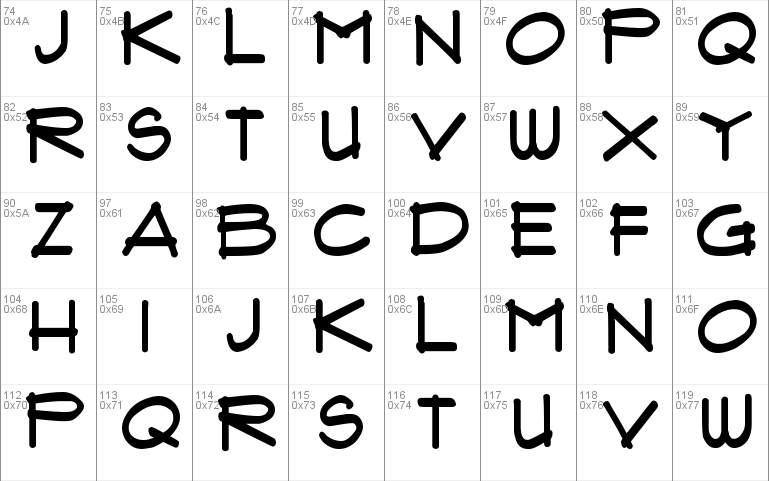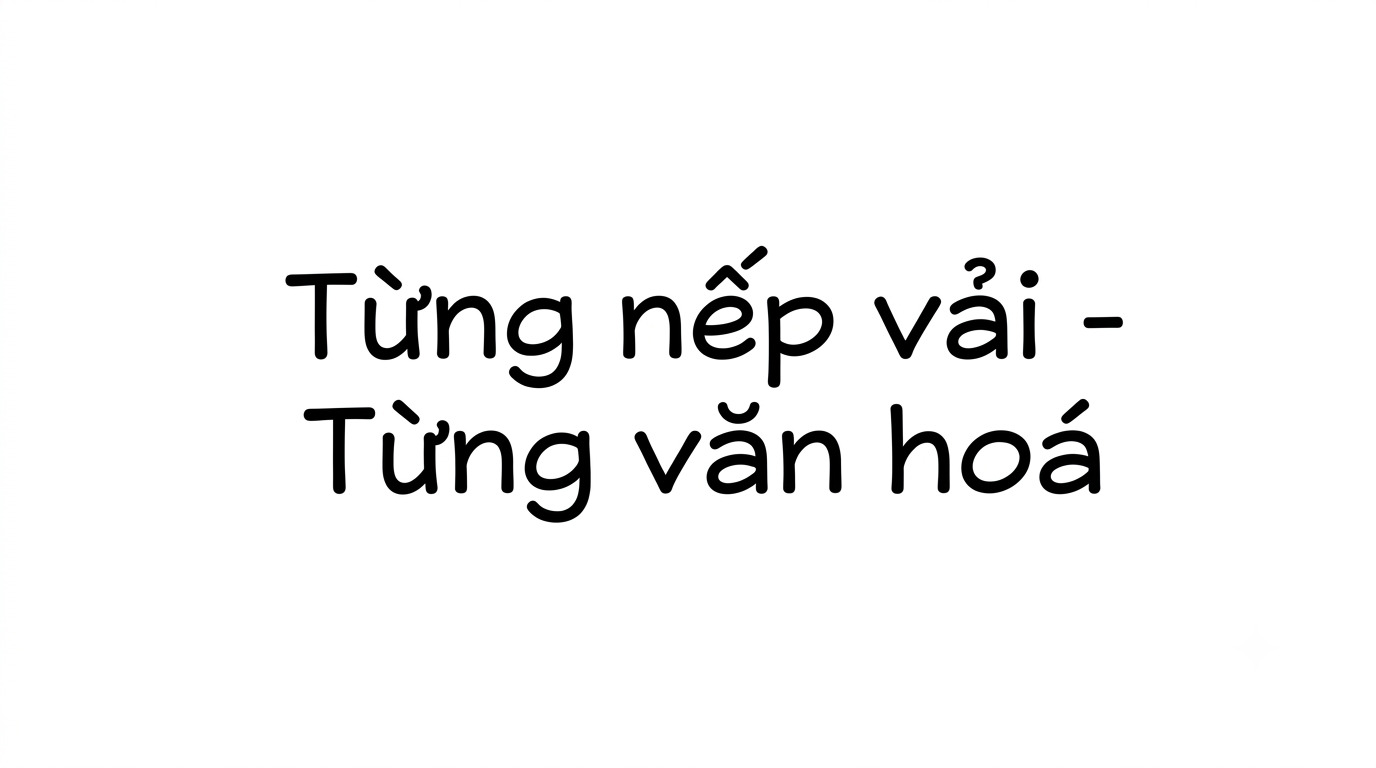
Font Flux Architect là gì?
Font Flux Architect là một phông chữ phong cách viết tay mô phỏng nét chữ của các kiến trúc sư trên bản vẽ kỹ thuật cổ điển. Đặc trưng của bộ chữ này là các đường nét dứt khoát, thanh thoát nhưng vẫn giữ được sự mềm mại tự nhiên, tạo cảm giác như được phác thảo trực tiếp bằng bút chì trên giấy can. Đây là sự lựa chọn cho các thiết kế hồ sơ năng lực công ty xây dựng, bìa bản vẽ, nhãn dán sản phẩm nội thất hoặc các mẫu quà tặng mang phong cách mộc mạc, hoài cổ.
Trong giới đồ họa, Flux Architect còn thường được tìm kiếm dưới tên gọi font architex hoặc các biến thể phông chữ kỹ thuật tương tự. Ưu điểm của dòng phông này là khả năng truyền tải thông điệp một cách chân thực, gần gũi nhưng vô cùng khoa học. Bản việt hóa tại In Viva đã được xử lý kerning cực chuẩn, đảm bảo các dấu thanh của tiếng Việt không bị chồng lấp lên các ký tự xung quanh, giúp bản thiết kế của bạn luôn rõ ràng và chuyên nghiệp trên mọi chất liệu.
Lưu ý: Khi bạn sử dụng font flux architect việt hóa cho thiết kế in ấn trên chất liệu gỗ hoặc kim loại, hãy chú ý đến độ tương phản để nét chữ viết tay không bị “nuốt” bởi vân gỗ hay bề mặt nhám.
5 Ứng dụng của font Flux Architect Việt hóa trong thiết kế và in ấn
Với phong cách chữ mô phỏng bản vẽ kỹ thuật và kiến trúc, Flux Architect giúp tạo dấu ấn riêng cho các ấn phẩm thương hiệu thuộc lĩnh vực xây dựng, nội thất và thiết kế:
- Thiết kế hồ sơ năng lực và bìa bản vẽ: Flux Architect phù hợp để sử dụng cho tiêu đề, tên dự án hoặc thông tin thương hiệu trên hồ sơ năng lực. Kiểu chữ mang hơi hướng kỹ thuật giúp tài liệu thể hiện sự chuyên nghiệp và đồng bộ với ngành kiến trúc, xây dựng.
- Khắc laser quà tặng gỗ doanh nghiệp: Logo hoặc tên thương hiệu dùng font Flux Architect khi khắc trên hộp trà gỗ, lịch gỗ để bàn hoặc bảng tên gỗ tạo cảm giác thủ công, gần gũi và phù hợp với các dòng quà tặng dành cho doanh nghiệp xây dựng, nội thất.
- Sản xuất bao bì sản phẩm nội thất và decor: Font chữ này có thể ứng dụng trên túi giấy Kraft, hộp giấy hoặc tem nhãn sản phẩm để thể hiện phong cách tối giản, phù hợp với các thương hiệu hướng đến thiết kế hiện đại và tinh tế.
- Thiết kế menu quán cafe phong cách Loft: Flux Architect Việt hóa phù hợp với các không gian mang phong cách công nghiệp, tối giản. Font có thể sử dụng trên menu gỗ, bảng thông tin hoặc các ấn phẩm trang trí giúp tăng tính đồng nhất cho không gian.
- In ấn quà tặng tri ân ngành kiến trúc: Lời chúc hoặc thông điệp sử dụng font Flux Architect khi in UV trên bình giữ nhiệt, sổ tay hoặc in nung trên bộ ấm chén sứ giúp món quà mang dấu ấn riêng dành cho kiến trúc sư, kỹ sư và đối tác.
5 lưu ý khi sử dụng font chữtrong in ấn
Để thiết kế sử dụng Flux Architect chuyển thành sản phẩm thực tế có độ rõ nét và phù hợp với từng phương pháp gia công, designer nên chú ý các yếu tố sau:
- Kiểm soát độ dày nét khi in ấn: Flux Architect có các đường nét mô phỏng chữ kỹ thuật tương đối mảnh. Khi in trên chất liệu có độ hút mực như giấy Kraft hoặc vải canvas, nên điều chỉnh độ dày Stroke phù hợp để hạn chế tình trạng mất nét.
- Tối ưu đường Path cho gia công bế nổi: Khi sử dụng Flux Architect để dập nổi logo trên hộp quà cao cấp, file vector cần được xử lý các điểm neo và đường nét nhỏ. Việc làm mượt đường Path giúp khuôn bế thể hiện rõ chi tiết chữ trên bề mặt giấy Ivory, giấy mỹ thuật hoặc carton lạnh.
- Lựa chọn kích thước chữ phù hợp: Flux Architect phù hợp với tiêu đề, logo hoặc các cụm từ ngắn. Với nội dung dài hoặc cỡ chữ quá nhỏ, các chi tiết kỹ thuật của font có thể làm giảm khả năng đọc khi in trên sản phẩm thực tế.
- Phối hợp màu sắc phù hợp với phong cách kiến trúc: Font này thường phù hợp với các gam màu như nâu gỗ, xám, đen, xanh đậm hoặc màu ánh kim. Việc lựa chọn màu sắc phù hợp giúp tổng thể thiết kế giữ được cảm giác hiện đại và chuyên nghiệp.
- Convert font trước khi gửi file sản xuất: Trước khi chuyển sang xưởng in, designer nên thực hiện lệnh Create Outlines để chuyển chữ thành dạng vector, hạn chế lỗi thay đổi font khi mở file trên các thiết bị khác nhau.